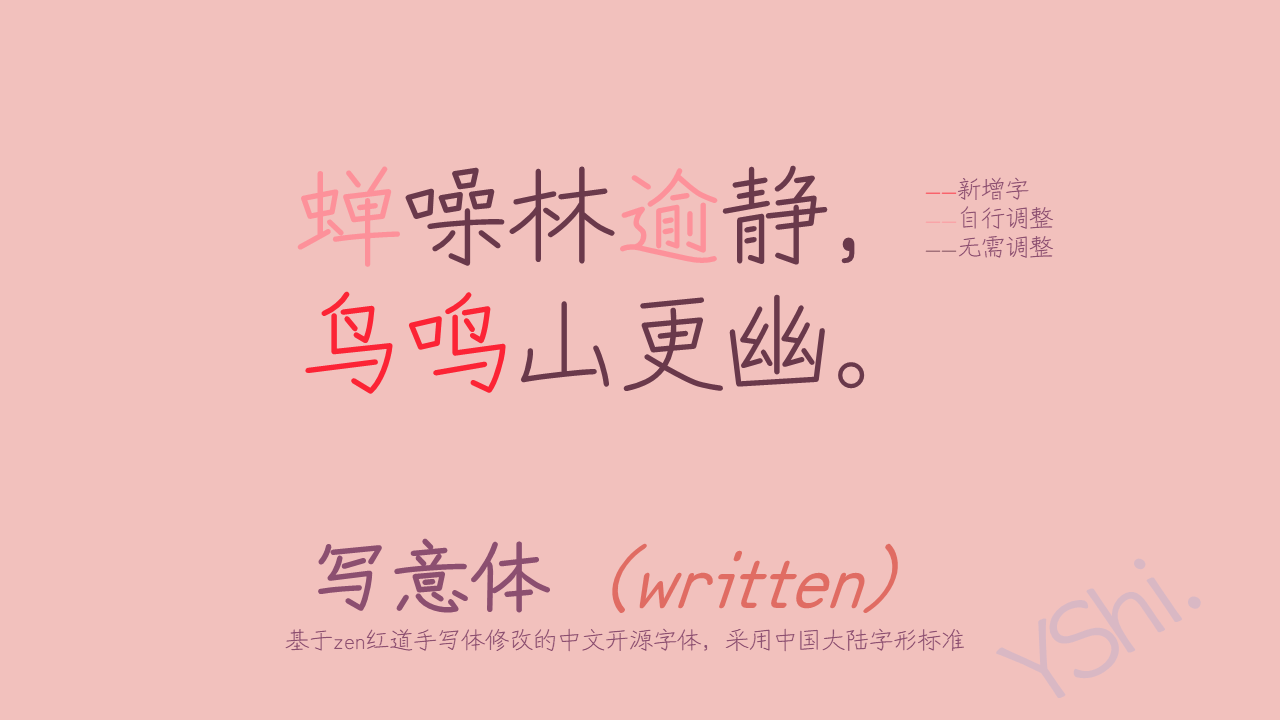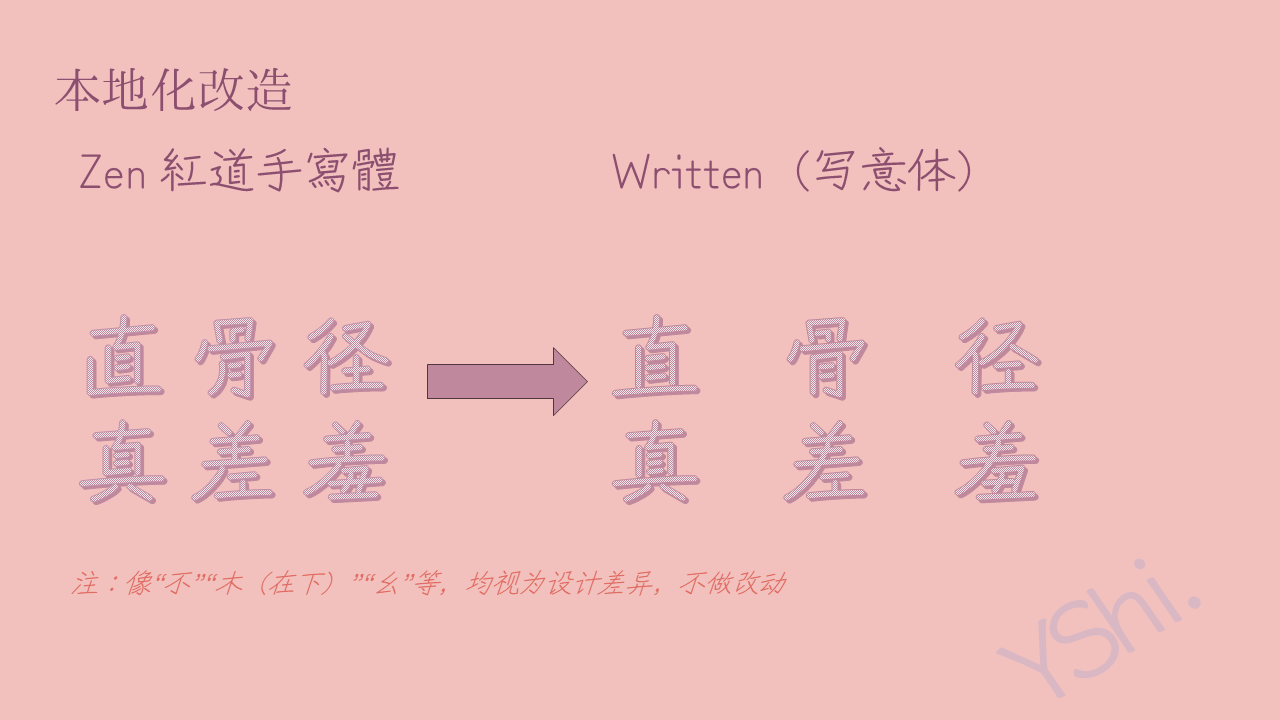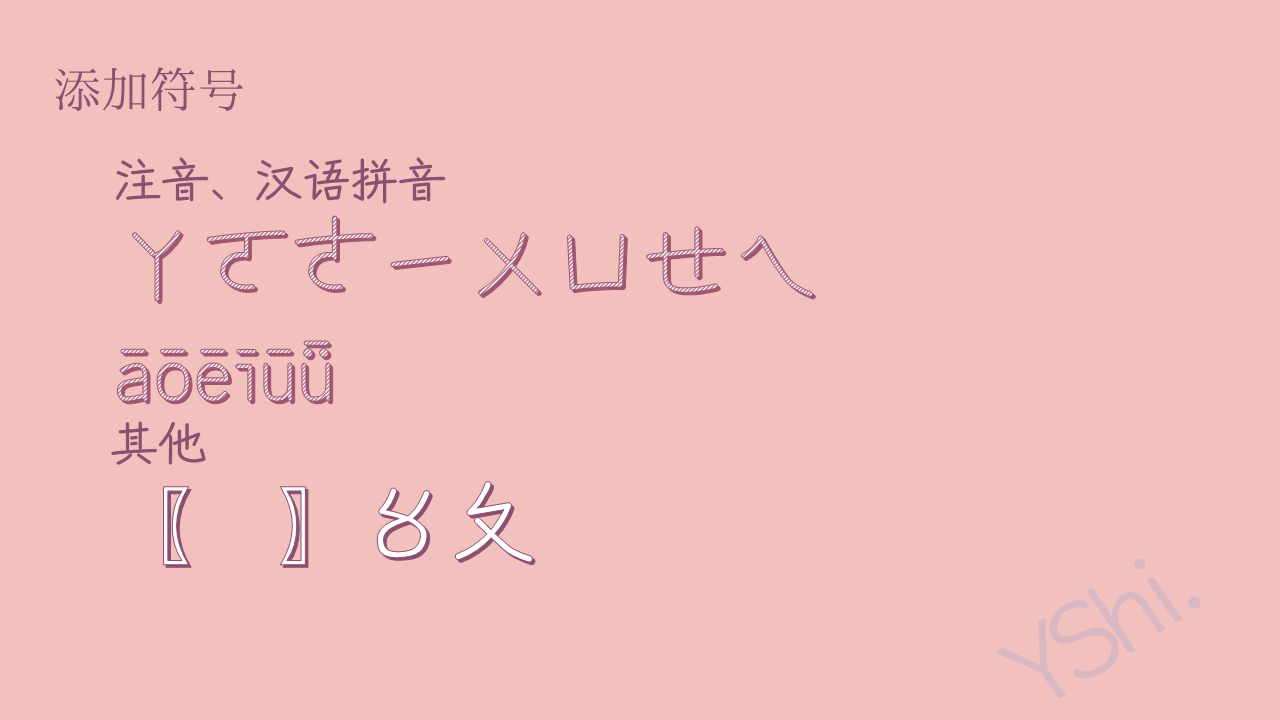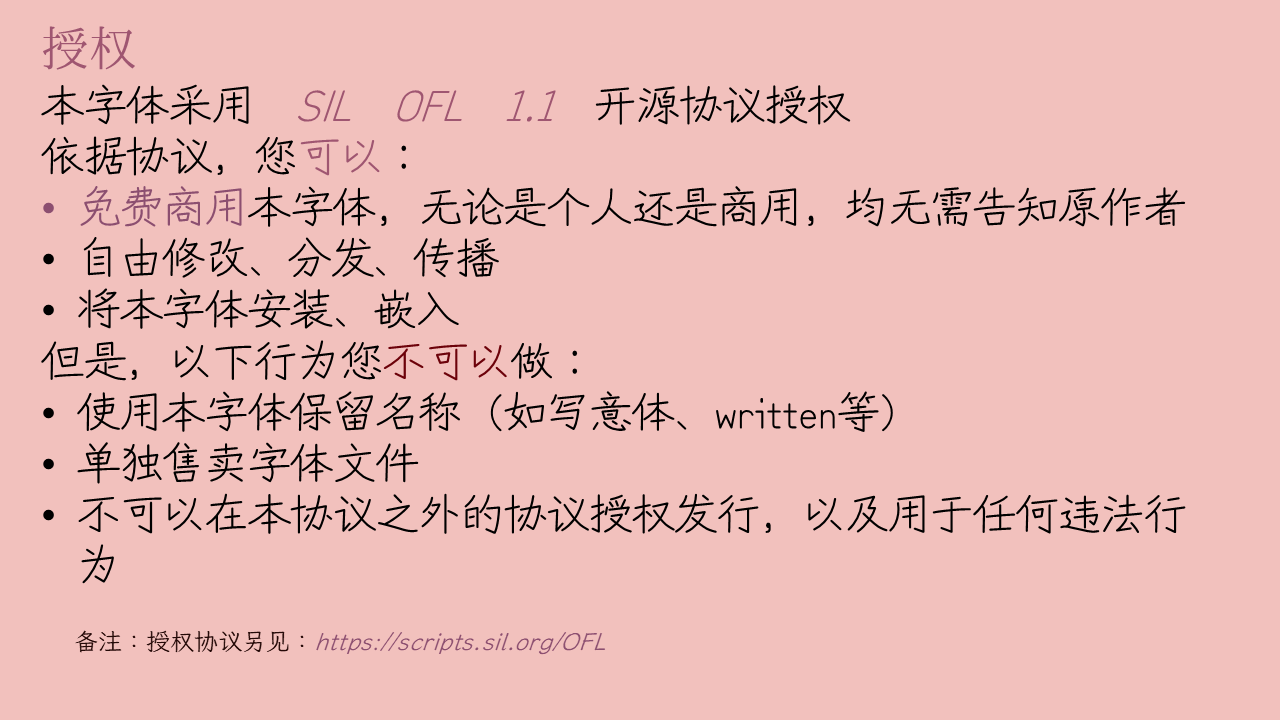
这是一段关于开源中文字体项目的说明。该字体以Zen红道手写体为基础进行改良设计,并严格遵循中国大陆现行的字形规范与标准。其设计初衷是呈现出一种贴近日常书写的效果,特别是模仿了中性笔(即水性笔或签字笔)书写时笔画粗细相对均匀、墨色流畅的自然质感。正因为这种鲜明的手写特性,该字体最初被命名为“Written”;后期开发中,为保持命名体系的一致性,恢复了“yshi”的前缀。其中文名称“写意体”则源于社区成员的建议,取自中国传统绘画中的“写意”精神,强调神韵与意境的传达,与字体随性、自然的风格相契合。 然而,该字体初始版本仅包含了一部分汉字字符,导致其无法完整、准确地显示所有简体中文内容,在实际应用中存在明显的局限性。为了解决这一问题,并进一步完善字形,本项目工程应运而生。其主要目标有二:一是系统地补全所缺失的简体中文常用字及次常用字,使字体能够满足绝大多数日常排版与显示需求;二是对特定字形进行精细调整与优化,例如对字母“G”等拉丁字母或相关符号的形态进行修改,使其在视觉风格上与中文部分的手写感更加协调统一,从而提升整套字体的美观度与实用性。